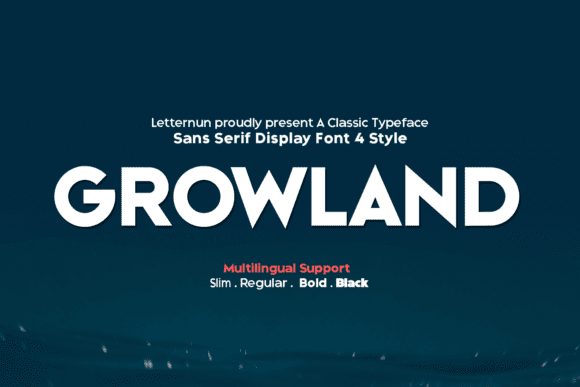
Название: Growland Font (2021)
Growland - это геометрический шрифт без засечек, который поставляется в 4 весовых стилях: Slim, Regular, Bold и Black.
Создан для любого профессионального проекта брендинга. Он идеально подходит для печати, брендинга и цитат. Хорошо работает в любом проекте графического дизайна и в качестве дисплейного шрифта.